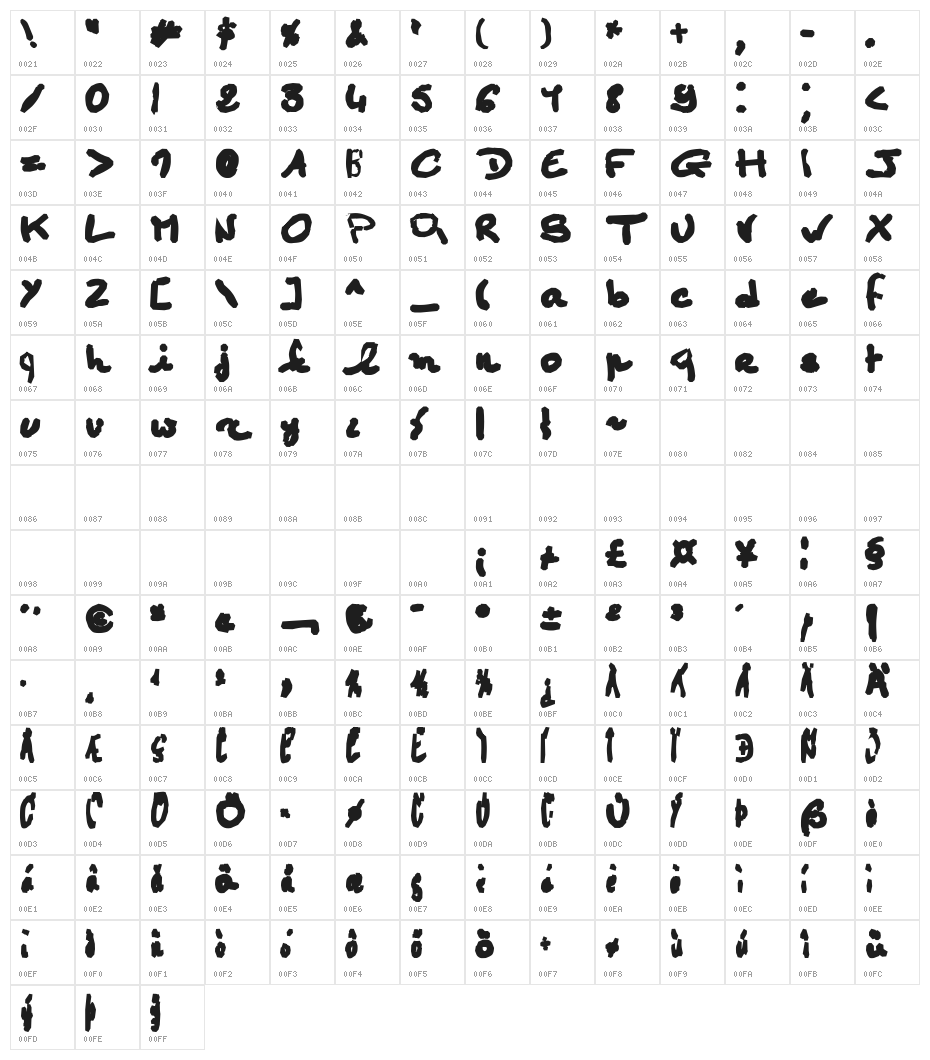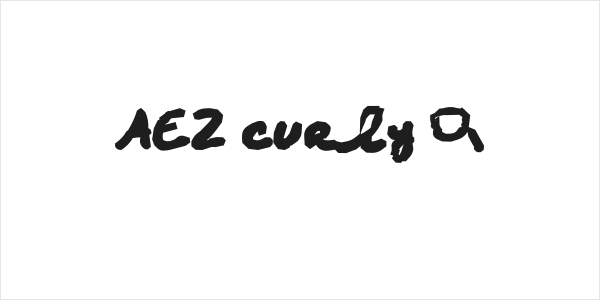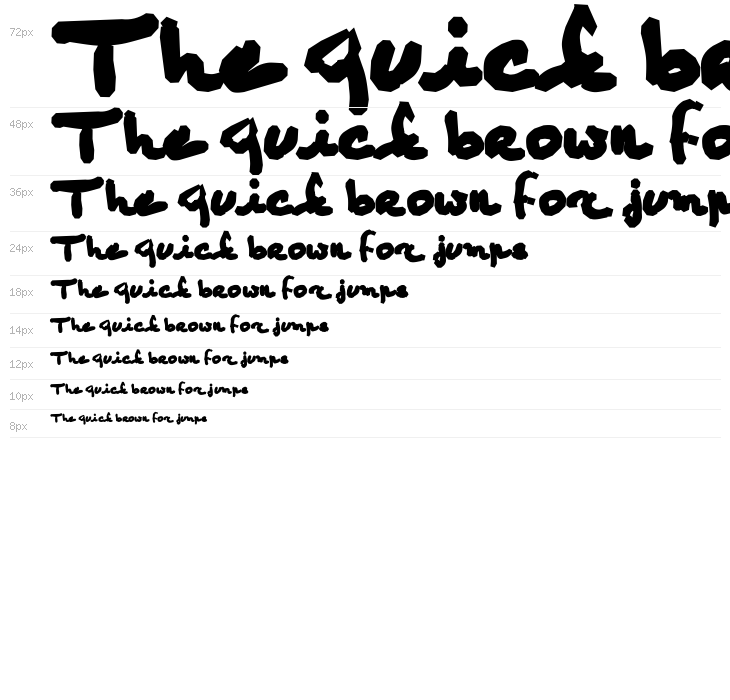
AEZ curly Q Font
| Stile generale | Artistic, Expressive |
| Caso d'uso | Headlines, Posters, Branding |
| Progetti proposti | Ideal for artistic posters, creative branding, and eye-catching headlines. |